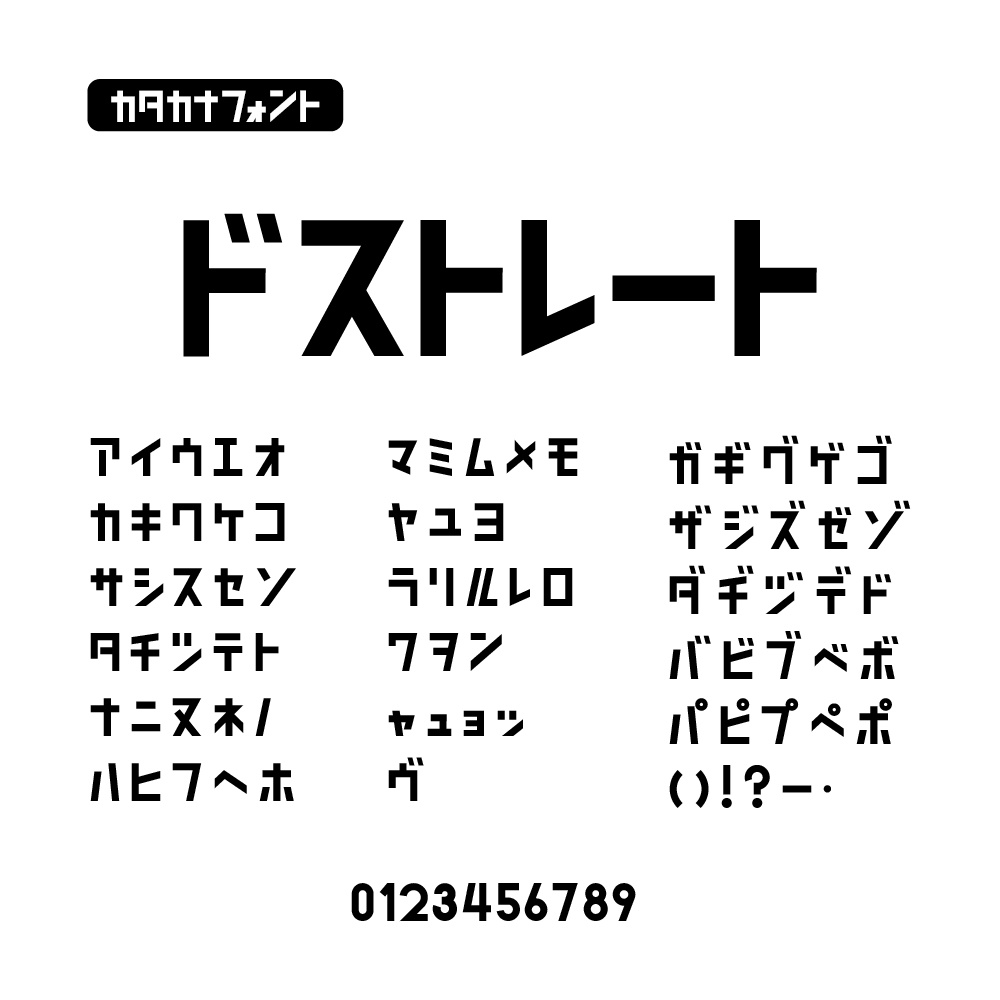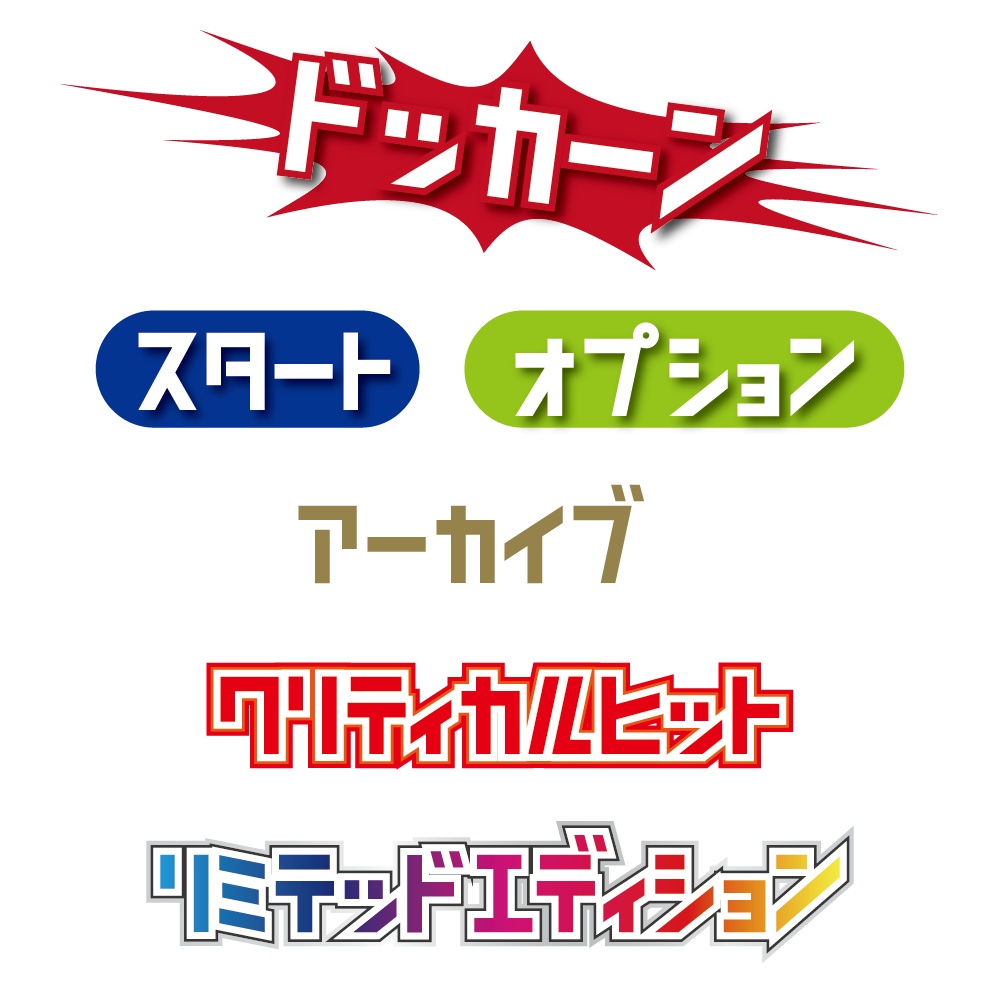
ドストレート(カタカナ専用フォント)
【概要】 太めで角ばったデザインが特徴のカタカナ専用フォントです。 直線的で幾何学的なフォルムが、モダンでクールな印象を与えます。 【収録文字】 ・全角カタカナ ・全角数字 0〜9 ・一部記号(ー()!?・ など、基本的な記号のみ) 【想定用途】 ・ゲームUI(ボタン、メニュー、技名表示) ・動画・配信サムネイル ・漫画・イラストの効果音、擬音表現 ・イベントロゴ、フライヤーの見出し ・アパレル・グッズデザイン ・Webサイトの見出し、バナー 【対応環境】 ・フォント形式:OpenType フォント(.otf) ・動作確認済み:Windows 10 / Windows 11(日本語版) ・上記以外の OS(macOS など)や一部アプリケーションでもご利用いただける場合がありますが、作者は動作保証・サポートを行っておりません。 【カーニングについて】 ・カタカナ向けのカーニング情報を含んでいます。 ・Adobe Illustrator / InDesign などの DTP ソフトでは、文字パネルの「カーニング」を「メトリクス」に設定してお使いください。 ・Web フォントとして利用することも可能ですが、カーニングの反映状況はブラウザや環境に依存します。 環境によってはカーニングが反映されない場合があります。 【ライセンス/利用範囲(有料版)】 ・個人・商用利用どちらも可能です。 ・本フォントを使用して作成したロゴ、画像、動画、印刷物などの成果物は、自由に配布・販売していただけます。 ・ただし、本フォントを使用して作成したロゴ・マーク等を商標登録・意匠登録することはできません。 ・フォントファイル自体の再配布・再販売、フォントデータを改変して別フォントとして再配布する行為は禁止です。 ・1 ライセンスにつき、ユーザーが所有または管理する 2 台までの PC でご利用いただけます(同時使用は同一ユーザーに限ります)。 ・詳しい条件は同梱の「EULA.txt」を必ずご確認ください。 【ファイル内容】 ・ドストレート.otf ・EULA.txt(利用規約) ・README.txt(概要と注意事項) 【注意事項】 ・本フォントおよび本フォントを用いて生成した画像・アウトラインデータを、機械学習・AI モデルの学習データとして使用することを禁止します。 ・フォントの表示結果やカーニングは、OS やアプリケーション、ブラウザ、描画エンジンの違いにより異なる場合があります。 必要に応じて文字間や行間を調整してご利用ください